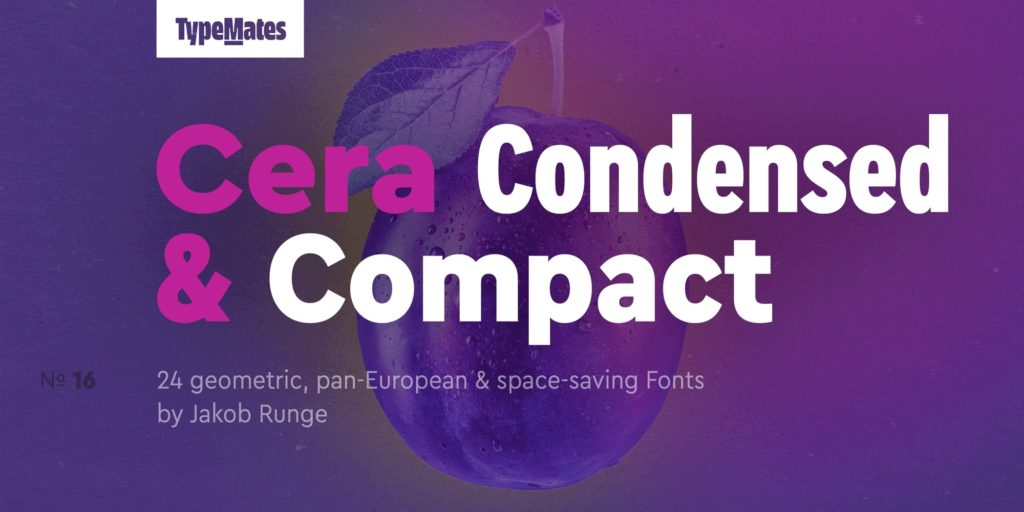
Это современный геометрический гротеск от французского дизайнера Оливье Гулино (Olivier Gulino). Отличается строгой геометрией, чистыми линиями и узким начертанием букв. Адаптирован для кириллицы, сохраняя узнаваемый стиль оригинала. Идеален для заголовков, где нужно сэкономить место или создать динамичный ритм. Скачать бесплатно можно только демо-версию; для коммерции требуется лицензия